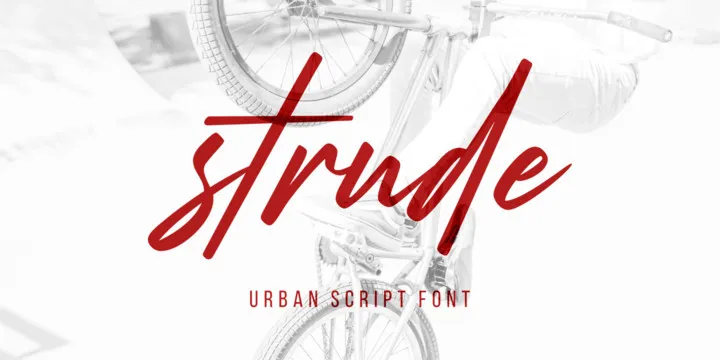
Este é o Strude Script Font, uma tipografia script elegante criada pela Letteralle, especialmente projetada para os designers e amantes da letra que buscam algo mais luxuoso e moderno. Através deste design sofisticado, a fonte oferece um resultado autêntico e contemporâneo, perfeito tanto para trabalhos de logotipo quanto para aplicativos em tela grande ou roupas personalizadas. O Strude Script vem com estilos set (maiúsculas e minúsculas), ligações interlinhas e suporte a múltiplas línguas, garantindo uma experiência fluida e versátil. Com letras distintivas que destacam seu estilo único, o Strude é perfeito para aplicativos de logotipo, materiais promocionais, exposições e até mesmo roupas personalizadas. Este font é uma escolha perfeita para aqueles buscando expressar algo mais autêntico em suas criações digitais.